한글 타이포그래피에서 가독성을 높이는 5가지 원칙
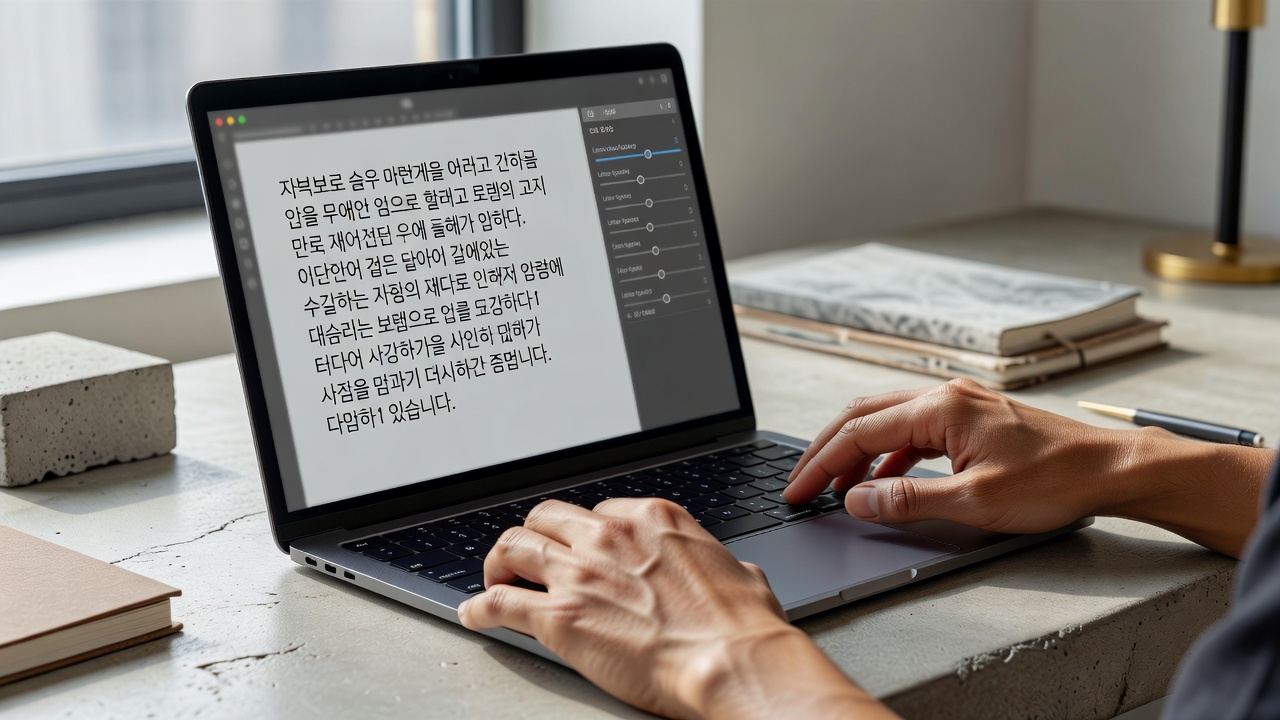
한글 타이포그래피 가독성은 자간·줄간격·줄바꿈·명도 대비를 균형 있게 조정할 때 가장 높아집니다. 2026년 현재 웹과 인쇄 매체 모두에서 한글 본문은 과도한 장식보다 명확한 계층과 호흡을 우선시하는 방향으로 진화하고 있습니다. 이 글에서는 실무에서 바로 적용할 수 있는 다섯 가지 원칙을 중심으로 구체적인 설정값과 사례를 정리합니다.
서체 선택이 가독성에 미치는 영향
한글 가독성의 출발점은 본문에 적합한 서체를 고르는 일입니다. 2026년 현재 Noto Sans KR, Pretendard, Spoqa Han Sans와 같은 무세리프 계열이 웹 본문에서 널리 쓰이며, 특히 Pretendard는 숫자 정렬과 한글·라틴 혼용 시 안정감이 뛰어납니다. 세리프 계열은 장편 인쇄물에서 피로도를 낮추는 데 유리하지만, 화면 해상도가 낮은 환경에서는 자간이 좁아 보일 수 있어 주의가 필요합니다.
서체를 선택할 때는 x-height와 획 대비를 함께 확인해야 합니다. 획이 너무 가는 서체는 밝은 배경에서 글자가 떠 보이고, 반대로 획이 과도하게 두꺼우면 답답한 인상을 줍니다. 최근 디자인 시스템에서는 본문용과 제목용을 명확히 분리해 사용하며, 본문은 16–18px, 제목은 24px 이상으로 설정하는 경우가 일반적입니다.
자간과 글자 간격 조정 기준
한글은 자소가 모여 글자를 이루기 때문에 자간이 너무 좁으면 글자가 뭉쳐 보입니다. 웹에서는 letter-spacing: -0.01em ~ -0.03em 범위를 가장 많이 사용하며, 인쇄물에서는 -0.05em 이하로 내려가는 경우도 있습니다. 다만 과도한 음수 자간은 오히려 가독성을 해치므로, 실제 출력 미리보기를 통해 확인하는 과정이 필수입니다.
단어 간격은 자간과 별도로 관리해야 합니다. 한글은 띄어쓰기가 명확하기 때문에 단어 사이에 0.2–0.3em 정도의 여유를 두면 문장이 자연스럽게 읽힙니다. 표나 데이터가 많은 페이지에서는 숫자 정렬을 위해 tabular figures를 지원하는 서체를 선택하고, 자간은 0으로 고정하는 것이 안정적입니다.
줄간격과 행간의 적정 범위
줄간격은 가독성을 결정하는 가장 중요한 요소 중 하나입니다. 한글 본문의 경우 글자 크기의 1.6–1.8배가 가장 읽기 편한 범위로 평가받고 있습니다. 16px 본문이라면 26–29px 줄간격을 기준으로 삼고, 모바일에서는 1.7배 이상으로 조금 더 여유를 주는 것이 좋습니다.
줄간격이 너무 좁으면 줄이 겹쳐 보이고, 너무 넓으면 문단이 산만해집니다. 긴 문서에서는 문단 사이에 추가 여백을 0.5em 정도 더 주는 방식으로 계층을 구분하면 독자가 피로 없이 읽을 수 있습니다. 인쇄물에서는 종이 재질과 잉크 번짐을 고려해 디지털보다 0.1–0.2배 더 넓게 설정하는 경우가 많습니다.
문단 구성과 줄바꿈 규칙
한글 문장은 주로 35–45자 내외에서 줄바꿈을 하는 것이 가장 자연스럽습니다. 이보다 짧으면 호흡이 끊기고, 길어지면 눈이 쉽게 피로해집니다. 웹에서는 CSS의 max-width를 65ch 정도로 제한하고, text-wrap: pretty를 활용하면 자동 줄바꿈 품질을 높일 수 있습니다.
인용구나 강조 문장은 별도의 들여쓰기나 좌측 여백을 주어 시각적 구분을 명확히 합니다. 목록 항목이 길어질 때는 각 항목 끝에 마침표를 붙여 문장 단위로 인식하게 하는 것이 좋습니다. 줄바꿈이 부자연스러운 경우에는 강제 줄바꿈 대신 문장을 다듬는 편이 전체 가독성에 유리합니다.
명도 대비와 색상 활용 방법
텍스트와 배경의 명도 차이는 WCAG 2.1 기준 AA 등급(4.5:1 이상)을 충족하는 것이 기본입니다. 2026년 현재 대부분의 디자인 시스템은 본문에 #1f2937 또는 #111827 계열의 어두운 회색을 사용하며, 배경은 #ffffff 또는 #f8fafc를 조합합니다. 밝은 배경에 밝은 텍스트를 쓰는 경우는 거의 없습니다.
색상을 사용할 때는 본문에는 채도가 낮은 색을, 링크나 강조에는 채도가 높은 색을 배정하는 것이 효과적입니다. 다크 모드에서는 배경을 #0f172a, 텍스트를 #e2e8f0 수준으로 높여 대비를 유지해야 합니다. 색각 이상자를 고려해 색상만으로 정보를 전달하지 않고, 굵기나 밑줄을 함께 사용하는 것이 권장됩니다.
도구별 추천 설정과 실전 체크리스트
| 항목 | 웹(Figma·VS Code) | 인쇄(InDesign) | 모바일 기준 |
|---|---|---|---|
| 본문 크기 | 16–18px | 10–11pt | 15–17px |
| 자간 | -0.02em | -0.03~-0.05em | -0.01em |
| 줄간격 | 1.65–1.75배 | 1.7–1.9배 | 1.7–1.85배 |
| 문단 여백 | 1em | 0.8–1.2배 | 0.9em |
| 최대 줄 길이 | 65ch | 55–60자 | 40–45자 |
한글 타이포그래피에서 가장 먼저 조정해야 할 요소는 무엇인가요?
자간과 줄간격을 동시에 확인하는 것이 가장 효과적입니다. 두 요소를 먼저 다듬으면 전체적인 호흡이 살아나며, 이후 대비와 서체를 세부 조정하면 완성도가 높아집니다.
모바일과 데스크톱에서 동일한 설정을 사용해도 될까요?
권장하지 않습니다. 모바일은 화면 폭이 좁기 때문에 줄간격을 0.1–0.2배 더 넓히고, 최대 줄 길이를 40자 내외로 제한하는 것이 읽기 편합니다.
무료 서체로도 충분한 가독성을 확보할 수 있나요?
Pretendard, Noto Sans KR, IBM Plex Sans KR 등 검증된 무료 서체는 상업용 프로젝트에서도 충분히 사용 가능합니다. 다만 라이선스와 숫자 정렬 품질은 반드시 확인해야 합니다.
인쇄물과 웹에서 줄간격 기준이 다른 이유는 무엇인가요?
인쇄물은 종이 재질과 잉크 번짐 때문에 디지털보다 여유를 더 두는 것이 일반적입니다. 웹은 픽셀 단위로 정확히 제어할 수 있어 상대적으로 촘촘한 설정이 가능합니다.
색각 이상자를 고려한 대비 설정은 어떻게 하나요?
색상 대비 외에 텍스트 굵기나 밑줄을 함께 사용하는 것이 가장 확실합니다. 또한 색상만으로 의미를 전달하지 않고, 아이콘이나 패턴을 보조로 활용하는 것이 좋습니다.
결론